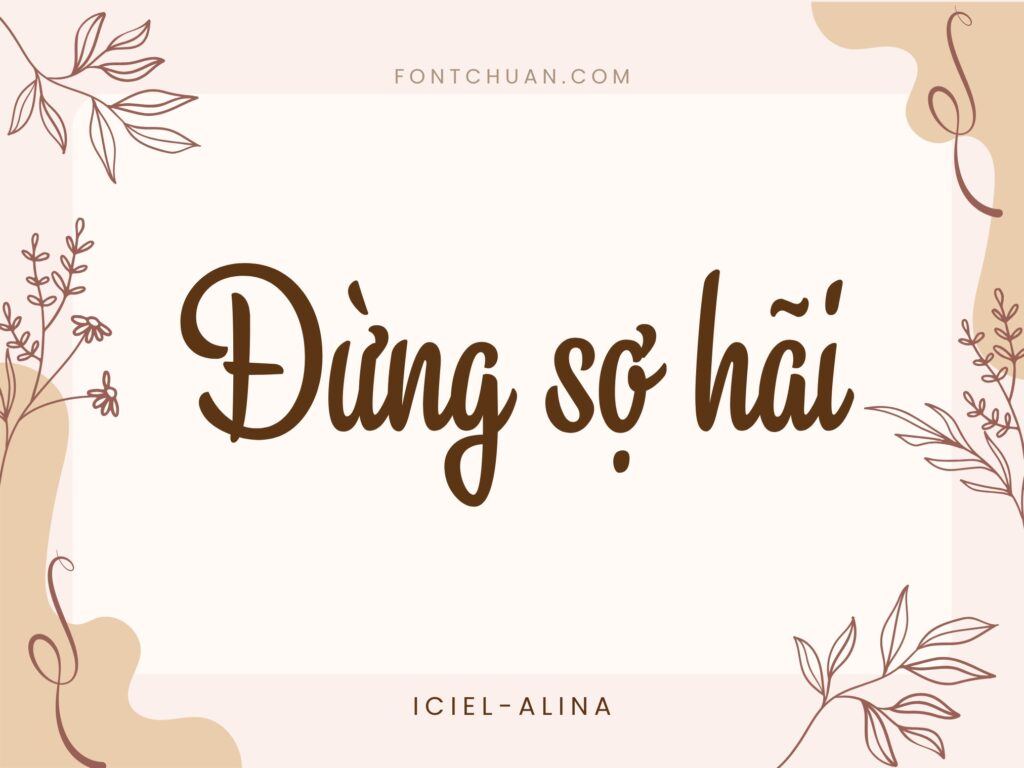
Font iCiel Alina Việt Hóa
Alina là một font chữ mang phong cách hiện đại với sự kết hợp giữa nét mềm mại và sự tinh tế trong từng ký tự. Font này được thiết kế để mang lại cảm giác nhẹ nhàng nhưng vẫn nổi bật, phù hợp với nhiều loại dự án sáng tạo khác nhau. Để hỗ trợ cộng đồng thiết kế Việt Nam, Iciel đã Việt hóa font Alina, giúp font này hỗ trợ đầy đủ tiếng Việt cùng hơn 200 ngôn ngữ khác. Phiên bản Alina Việt hóa đã được thành viên Font Chuẩn sưu tầm và đăng tải, nhằm mang đến sự lựa chọn phong phú hơn cho các nhà thiết kế.
Về đặc điểm thiết kế, Alina sở hữu những đường nét uyển chuyển nhưng vẫn giữ được độ sắc nét, giúp tạo sự cân bằng giữa tính thẩm mỹ và tính dễ đọc. Font này rất phù hợp với các thiết kế mang phong cách nghệ thuật, thiệp cưới, thương hiệu thời trang và typography sáng tạo. Ngoài ra, Alina cũng là một lựa chọn lý tưởng cho các ngành nghề như quảng cáo, giáo dục và ẩm thực, mang đến phong cách tinh tế và chuyên nghiệp. Font này cũng rất thích hợp để sử dụng trong các sự kiện như Valentine, Sinh nhật và các dịp lễ hội.